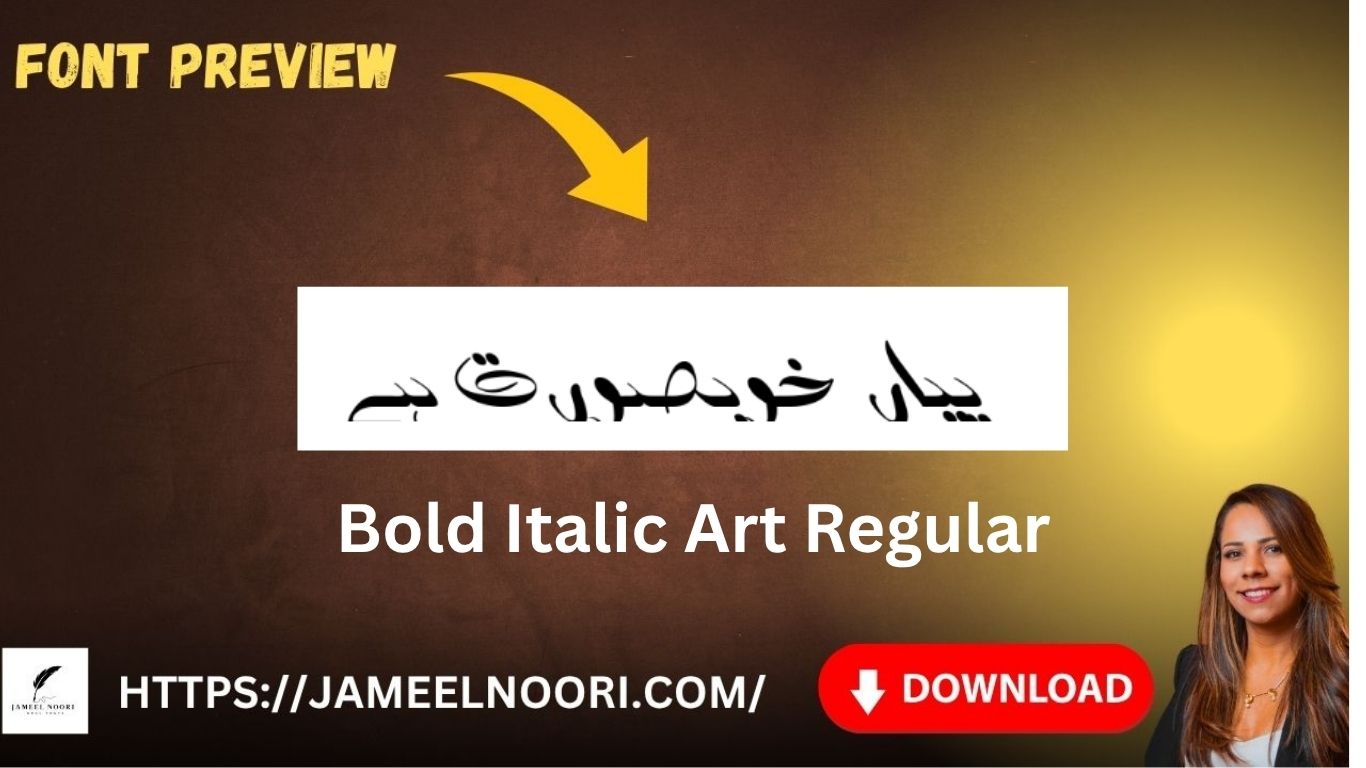
Download Urdu Font Bold Italic Art Regular
Introduction – Download Urdu Font Bold Italic Art Regular
Agar aap Urdu aur English dono zabanoon mein likhne ke liye ek stylish aur artistic font dhoondh rahe hain, to Download Urdu Font Bold Italic Art Regular aap ke liye perfect choice hai. Yeh font un users ke liye bohat hi mufeed hai jo Urdu design projects, headings ya logo creation ke liye ek visually appealing font chahte hain.
Features of Download Urdu Font Bold Italic Art Regular
Stylish bold aur italic design
Urdu aur English text ke liye suitable
Why Choose Download Urdu Font Bold Italic Art Regular?
Bold Italic Art Regular font ka unique look isay headings aur logo design ke liye ideal banata hai. Yeh font Urdu likhne ke traditional andaaz ko ek modern touch deta hai, jo websites, graphics, aur social media creatives mein use hota hai.
Uses of Bold Italic Art Regular
Yeh font aap istarah use kar sakte hain:
Urdu aur English headlines
Invitations aur greeting cards
YouTube thumbnails aur banners
Logos aur branding designs
Calligraphy-style projects
Pros and Cons
✅ Pros
Stylish aur artistic design
Urdu ke sath English compatibility
❌ Cons
Sirf limited glyphs
Body text ke liye mushkil ho sakta hai
Bold Italic Art Regular font ek aisa Urdu font hai jo aapke text ko artistic aur stylish banata hai. Chahe aap graphic designer hain ya content creator, yeh font aapke kaam ko nayi pehchan de sakta hai. Isay download karke apne creative projects mein use karein aur farq khud mehsoos karein.
What is Bold Italic Art Regular font used for?
It is used for Urdu and English headlines, graphics, and calligraphic styles.
Is this font suitable for body text?
Not ideal. It’s more suitable for headings and titles.